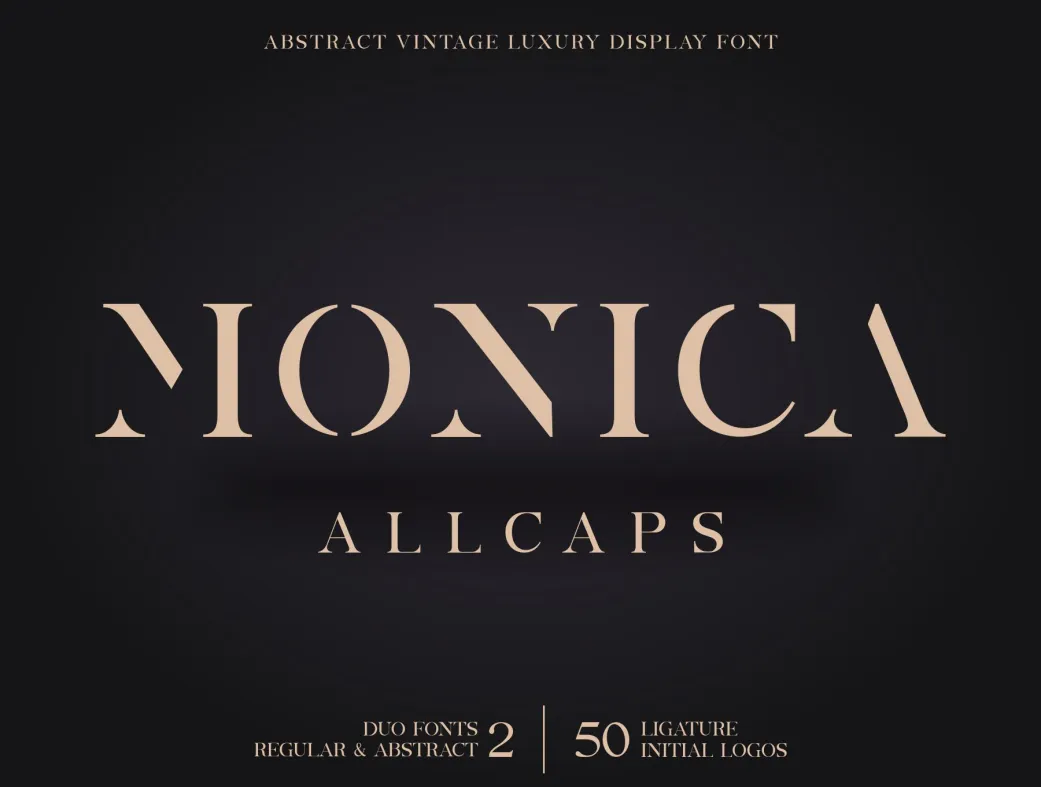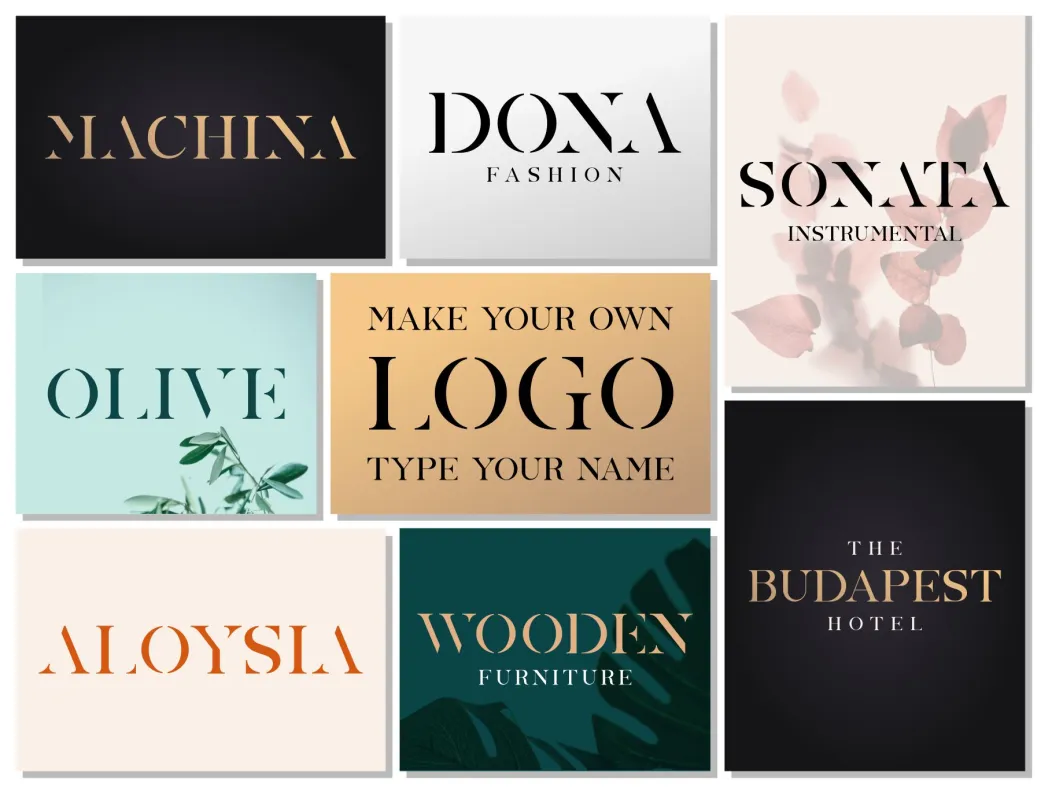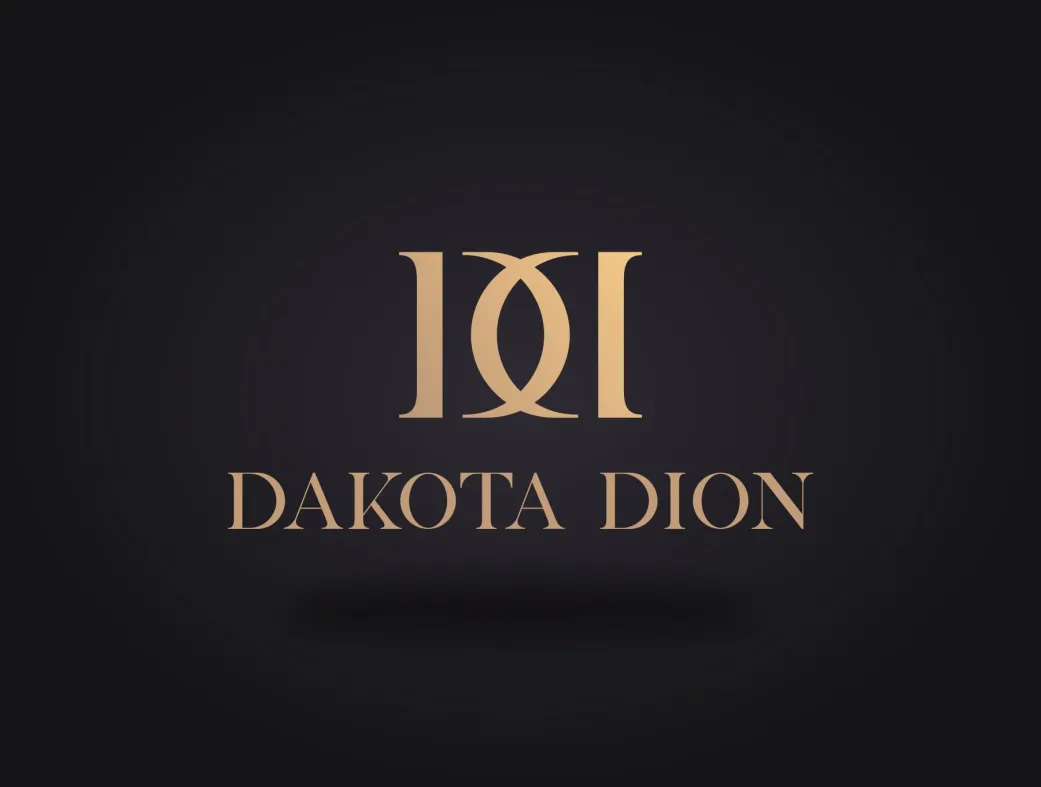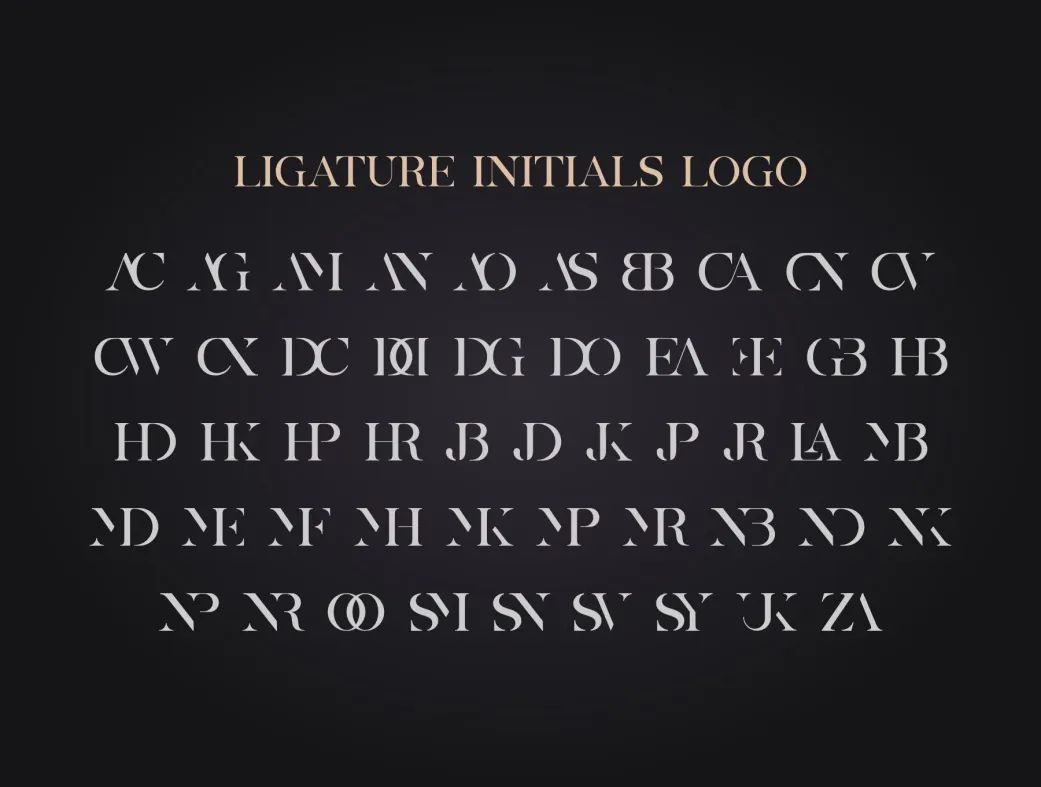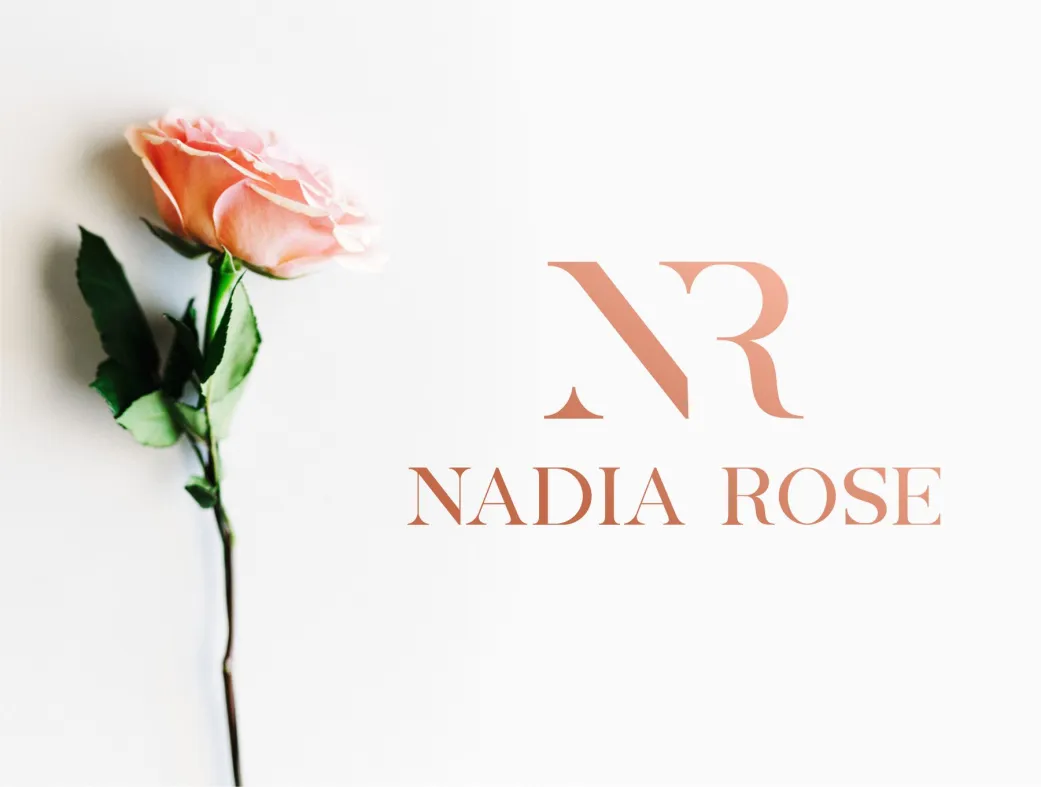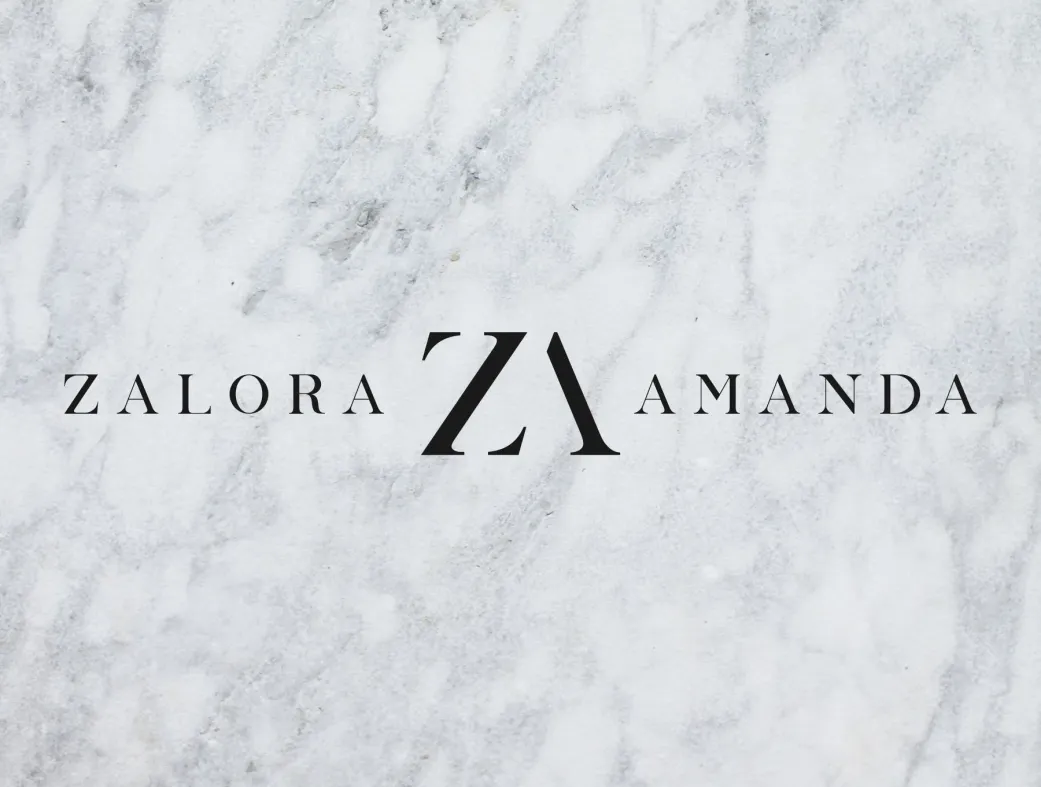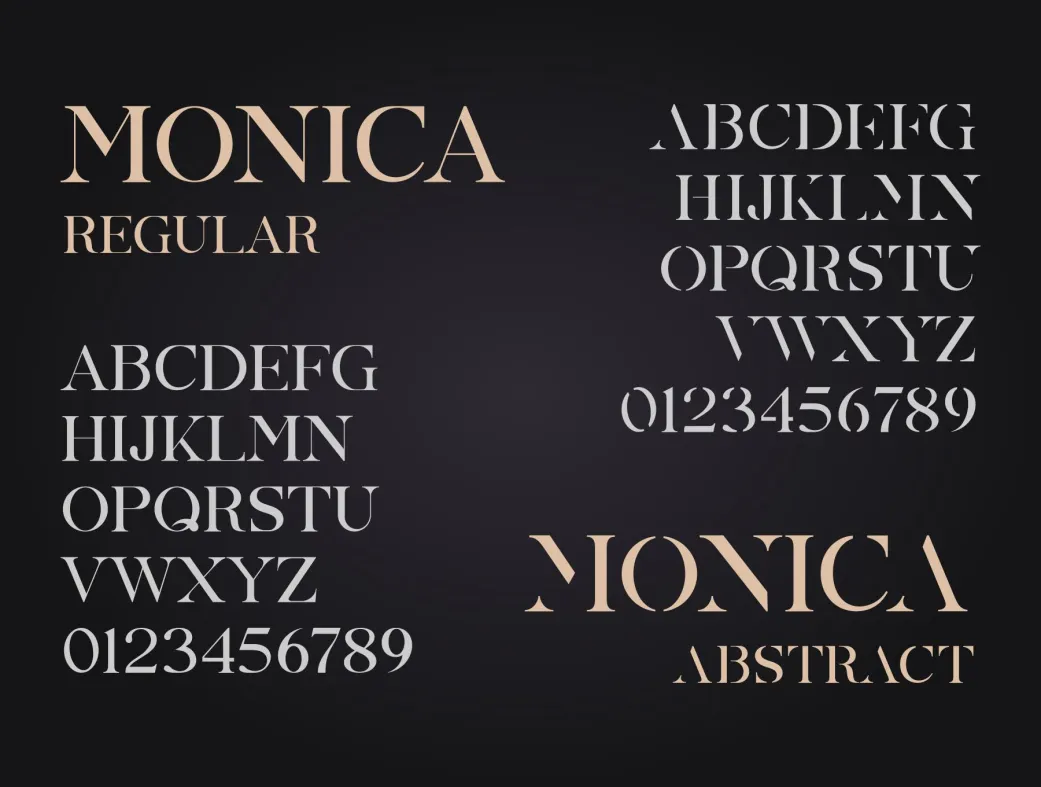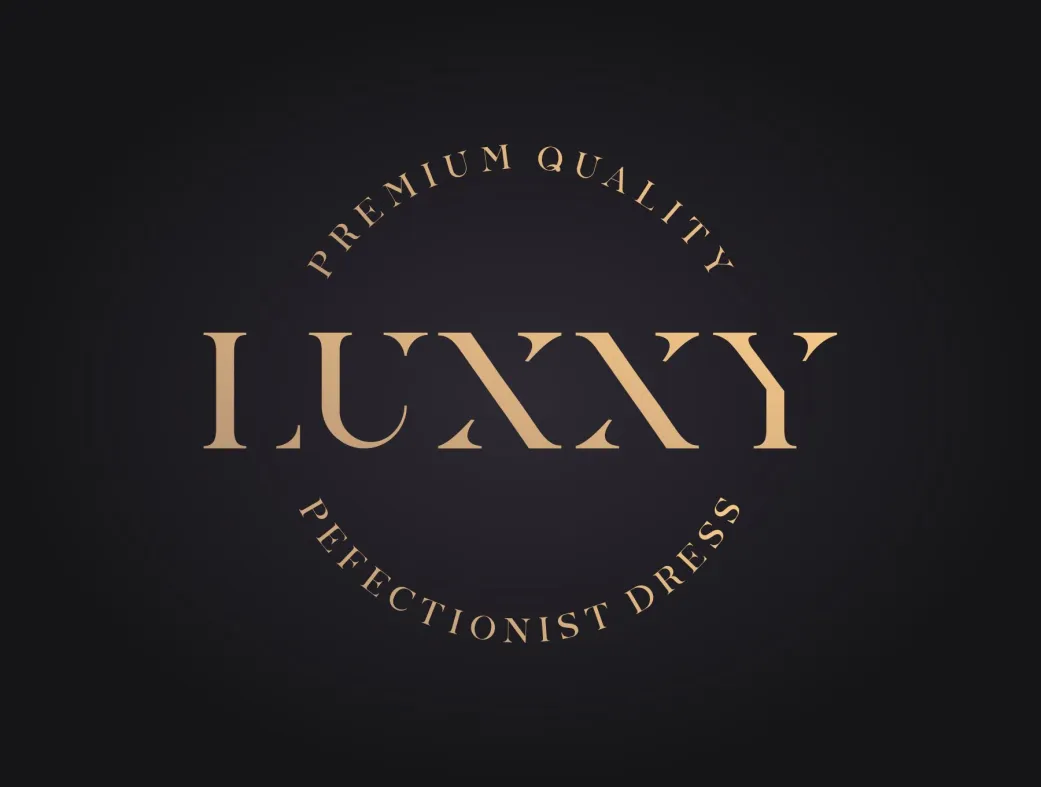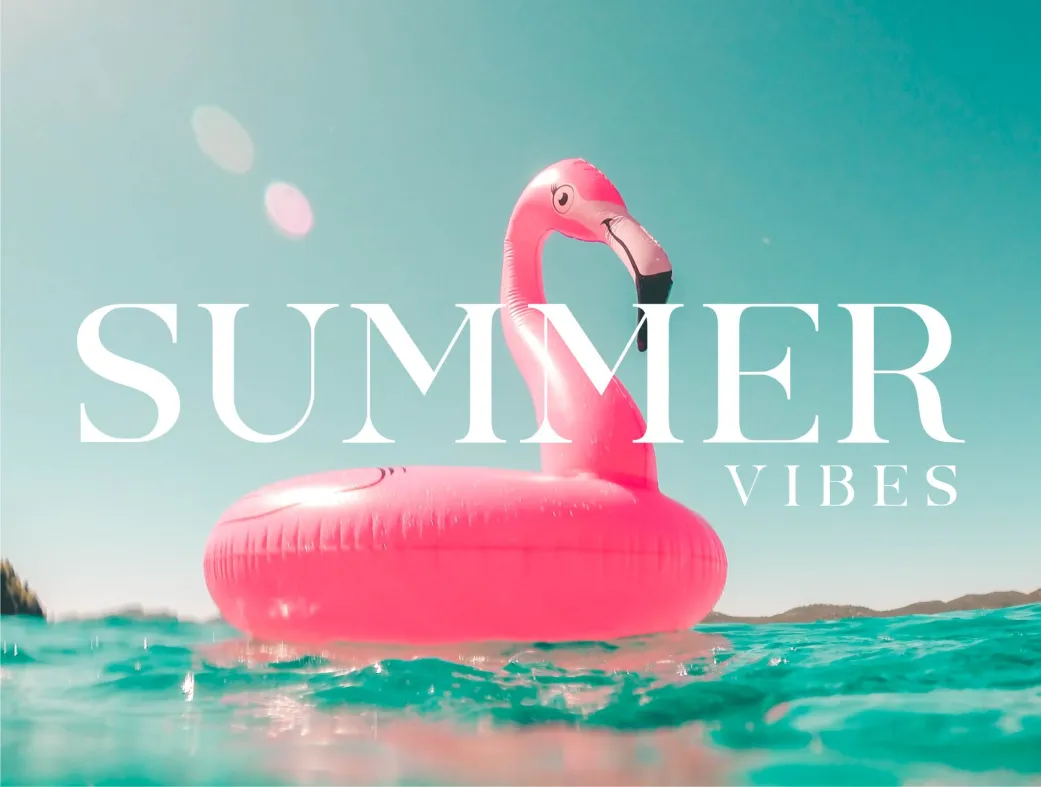
خانواده فونت مونیگا آل‌کپس | Monica Allcaps
آیا به دنبال فونتی لوکس و وینتیج برای پروژه‌های خلاقانه‌تان هستید؟ فونت مونیگا آل‌کپس با طراحی منحصر به فرد و حروف بزرگ، جلوه‌ای خاص به لوگوها و پوسترهای شما می‌بخشد.
Monica Allcaps Fonts Family
خانواده فونت مونیگا آل‌کپس | Monica Allcaps | فونت نمایش مونیگا آل‌کپس
فونت مونیگا آل‌کپس یک فونت نمایش لوکس و وینتیج است که با طراحی زیبا و شیک خود، به پروژه‌های شما جلوه‌ای خاص می‌بخشد. این فونت شامل دو نوع مختلف، یعنی مونیگا آل‌کپس معمولی و مونیگا آل‌کپس انتزاعی است که هر دو به صورت حروف بزرگ طراحی شده‌اند و می‌توانند در طراحی لوگو، پوستر، تیتر و موارد دیگر استفاده شوند.
فونت مونیگا آل‌کپس دارای طراحی وینتیج و کلاسیک است که آن را به گزینه‌ای عالی برای طراحان حرفه‌ای و مبتدی تبدیل می‌کند. این فونت به دلیل سبک حروف بزرگ و وجود لیگاتورها، قابلیت استفاده در طراحی لوگوهای منحصر به فرد و جذاب را دارد. با ویژگی‌های OpenType، کرنینگ و لیگاتورها، این فونت به سادگی می‌تواند در پروژه‌های مختلف به کار رود.
فونت مونیگا آل‌کپس شامل حروف بزرگ، اعداد، نشانه‌گذاری و پشتیبانی چند زبانه است که به شما این امکان را می‌دهد تا با خیال راحت از آن در پروژه‌های بین‌المللی خود استفاده کنید. طراحی انتزاعی آن به ویژه برای پروژه‌های مد و طراحی‌های خلاقانه بسیار مناسب است و می‌تواند توجه مشتریان را به خود جلب کند.
این فونت برای طراحان گرافیک، عکاسان، و برندها ایده‌آل است. می‌توانید از آن در طراحی لوگوها، پوسترها، بسته‌بندی محصولات، و تیترهای جذاب استفاده کنید. برای کاربران مبتدی، پیشنهاد می‌شود که ابتدا با طراحی ساده شروع کرده و به تدریج با ویژگی‌های پیشرفته‌تر فونت آشنا شوند.
2. این فونت چه زبان‌هایی را پشتیبانی می‌کند؟فونت مونیگا آل‌کپس از چندین زبان پشتیبانی می‌کند، از جمله زبان‌های لاتین و برخی زبان‌های دیگر.
5. آیا این فونت دارای ویژگی‌های خاصی است؟بله، فونت مونیگا آل‌کپس دارای ویژگی‌های OpenType، کرنینگ و لیگاتورها است که به طراحی‌های شما زیبایی و جذابیت می‌بخشد.